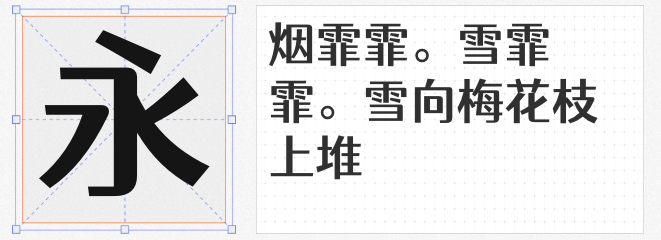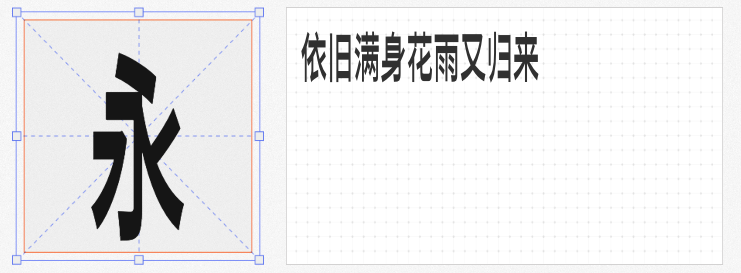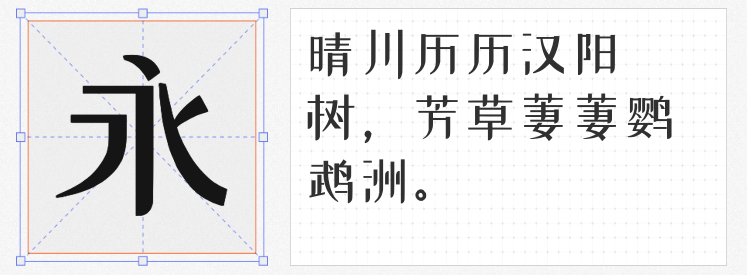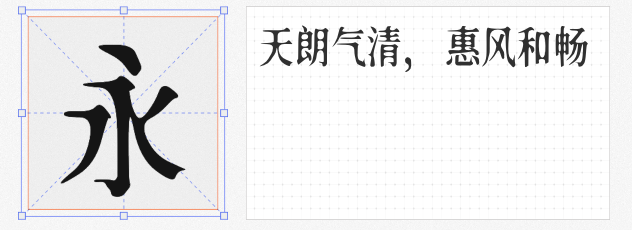
在视觉设计中,标题字体是传递品牌调性、吸引用户注意力的核心元素。本文精选四款风格独特且可免费商用的中文字体,涵盖沧桑古韵、现代锐利、未来科技与人文温度,助力设计师突破创意边界。
由网友@新愚公基于思源宋体改造,这款字体通过随机扭曲与笔画断裂效果,模拟出古印章历经风霜的质感。其方正雅观的字形结构,即使缩小至12号仍清晰可辨,尤其适合文化类海报、复古包装及影视标题设计。
设计师李大卫为女儿三周岁创作的礼物,同时填补了免费LOGO体市场的空白。其笔画如剑身般修长挺拔,通过简化部分笔画提升识别性,却未牺牲设计感。
基于思源黑体改造的逆反差风格字体,通过“上窄下宽”的笔画结构打破传统黑体的平衡感。Compact窄体版本进一步压缩字宽,强化科技感与前卫气质,适合游戏界面、科幻电影海报等场景。
仓耳字库在疫情期间推出的公益字体,融合宋体的文雅与黑体的力量感,通过圆角处理笔画转折,传递“刚柔并济”的东方哲学。其家族包含5个字重,可满足从标题到正文的层次需求。公益海报使用仓耳渔阳体 W04粗字重作为主标题,搭配细字重正文,既能突出核心信息,又保持整体和谐。